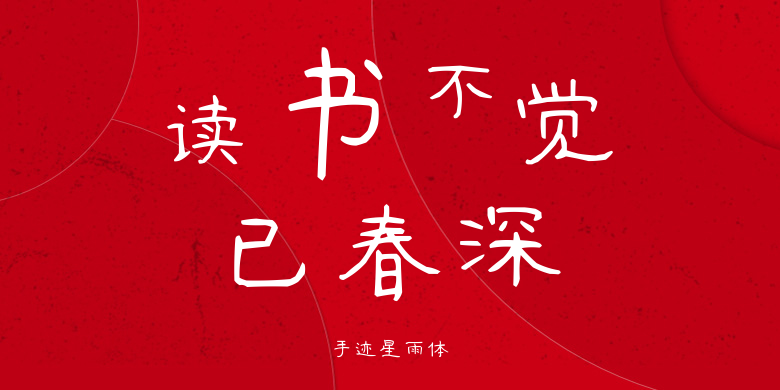
手迹星雨体
手迹星雨体,这款字体结构工整、笔画清晰,兼顾美观与易读性,适用于标题、正文、海报、包装、LOGO 等多种场景。字形优雅稳定,风格百搭耐看,适配日常排版与创意设计,让文字呈现更舒适、更具质感。手迹星雨体一笔一画,皆是细节,以均衡的比例、流畅的线条打造舒适视觉体验,字形端正大气,风格简约现代。无论是商业设计、品牌宣传还是日常排版,都能轻松驾驭,让文字更有格调与力量。手迹星雨体字体下载。